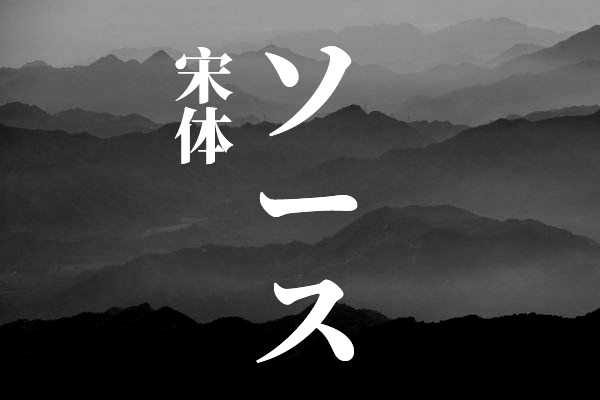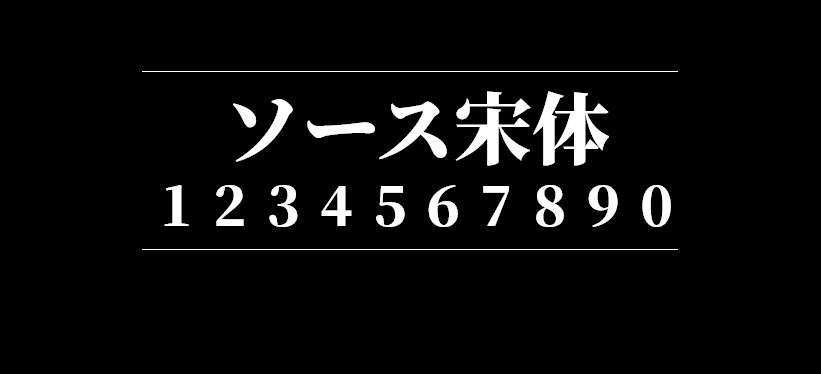
思源宋体-日文版字体介绍
谷歌联合Adobe发布的全新开源字体——思源宋体(Source Han Serif),支持四种不同的东亚语言——简体中文、繁体中文、日文和韩文,同时还提供七种字体粗细形式的共65,535个字形(OpenType 格式支持的最大上限),以保证视觉审美上的一致性,同时可以满足各种不同的排版需求。 关于这4种语言的字形,看似有些是相同的中文字体,实际上可能有多达四个区域差异化的字形设计。思源宋体涵盖所有这些字形变体并且精心地设计了这些区域化字形。
思源宋体(英文名:Source Han Serif)是由Google与Adobe联合发布的泛CJK开源字体,隶属于Noto字体项目,旨在消除多语言文本中因缺字导致的空白“豆腐块”现象。该字体与思源黑体构成配套字体组合,响应东亚地区对统一字体设计的需求,服务于15亿人口。
思源宋体-日文版字体应用示例